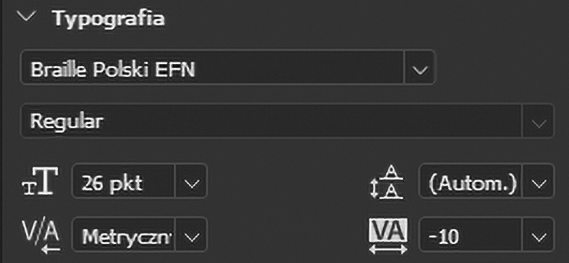
Podstawą systemu pisma Braille'a jest sześciopunkt nazywany znakiem tworzącym. System składa się ze znaków będących kombinacją sześciu wypukłych punktów ułożonych w dwóch kolumnach. Kombinacja i rozmieszczenie punktów daje możliwość zapisu wielu znaków.
Bazę alfabetu stanowi pierwszych 25 znaków oraz jeden oznaczający literę w:
Warto zwrócić uwagę, że litery k do t są takie jak litery a do j, ale z dodanym punktem w lewym dolnym rogu. Ponadto litery u do z (bez w) są takie jak k do o, ale z drugim punktem na dole.
Oto prosty system Braille'a! Litera w została dodana później i ma osobny wzór.
Aby dopełnić swej prostoty, wzory cyfr są identyczne jak pierwszych 10 liter — a do j.
Dlatego, aby odróżnić liczby, należy przed pierwszą cyfrą wstawić znak pomocniczy # [liczba].
Wzory dużych liter są takie same jak małych, aby więc wyróżnić wielką literę (wymaganą np. przy oznaczaniu witamin) trzeba ją poprzedzić pomocniczym znakim ^ [duża litera].
Teraz, taka treść, zamieniona na alfabet Braille'a, będzie prawidłowa:
Wzory polskich znaków diakrytycznych:
W kroju Braille Polski EFN można użyć domyślnych odstępów między znakami, lub je zmienić (zmniejszyć lub zwiększyć) we właściwościach tekstu w edytorze:
Aby to zrobić, należy zaznaczyć edytowany tekst, następnie w panelu Typografia ustawić kerning na „Metryczny”. W polu wyboru „VA” można dowolnie zmienić odstępy między znakami, stosownie do konkretnych wytycznych lub projektu.